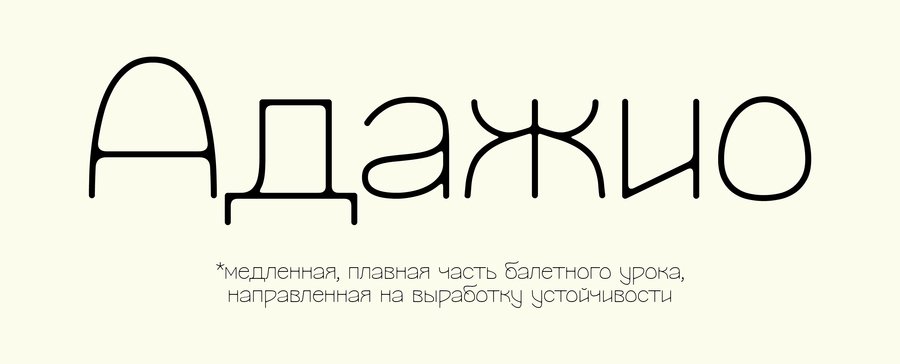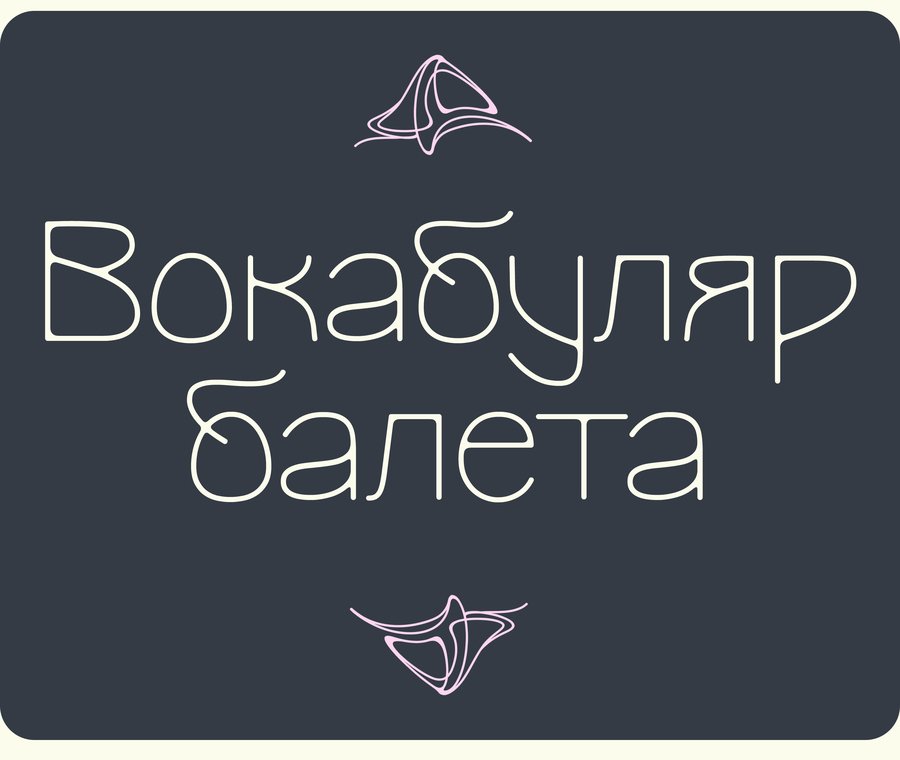
Tactus font
Tactus (От лат. tactus — прикосновение, осязание) — шрифт гротеск без видимого контраста. Отличается тонкостью линий и закругленными углами.